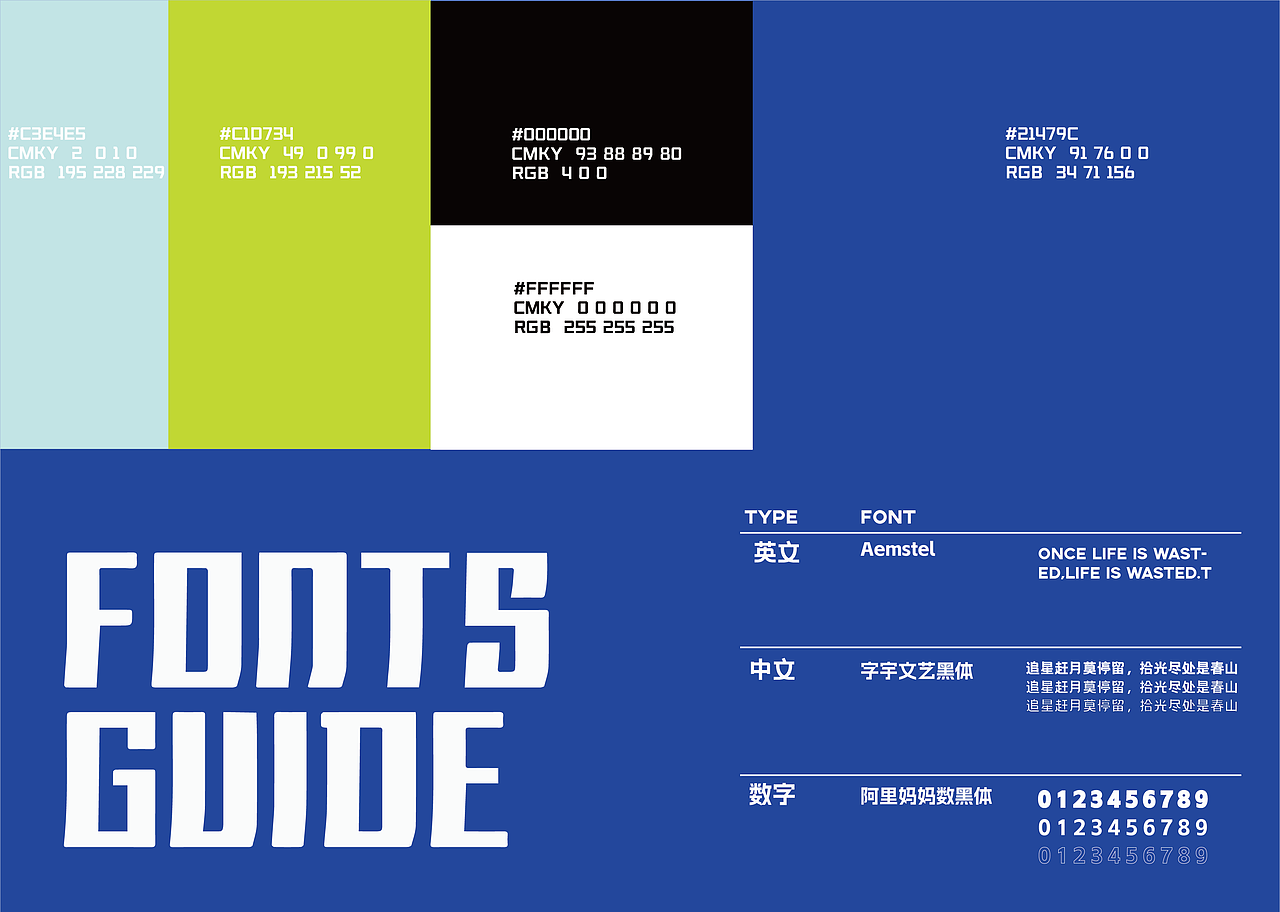
零基础第一份作品集
记录一下去年三月份天天九点实习结束,路过天空之城后去南山书房待到十二点挤出来的作品集——看不清前路还能努力向前的日子。其中logo部分做到最后完全没想法基本都算二创临摹了><
字体有点太多,相关经历不够详细具体——那个时候连六级都没过就一个人千里走单骑了
装饰性的小字过于小,白字阅读性较差
英文slogan硬翻
字体应该统一,应该用色块增加层次
图形太多,功能性图标与宣传性图标应作区分,分出主次
图片可以优化一下,logo放的太满太大
右个人介绍部分做的太分散
背景颜色不统一,那张打印纸有点假
字体太大 太满
缺少留白
logo不够简约,文字过多无重点,整体板块排版不舒展
IP设计是这个作品集最感兴趣的部分,现在看也觉得很可爱的
内容与APP联系弱,应该是类似“该吃药了”等内容
行间距太宽,可能是一直不喜欢写设计说明的原因
背景颜色切换比较突兀
右边比较菜,无重点,可读性差
灵感枯竭,二创部分,侵删